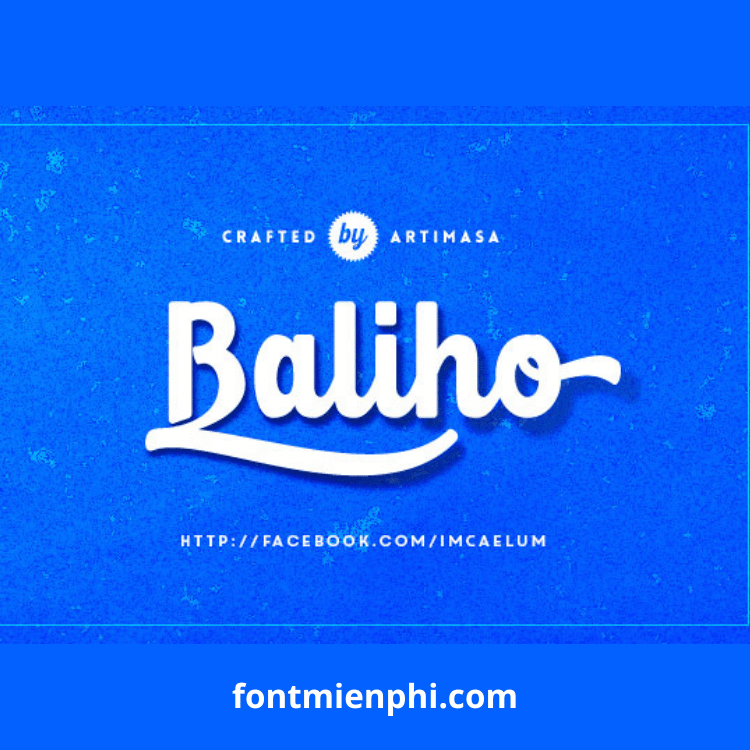
Việt hóa font iCiel Baliho Script
Font iCiel Baliho Script là một trong những font chữ nghệ thuật, phong cách brush script đẹp mắt, thích hợp cho thiết kế logo, poster, bìa sách, quảng cáo và các dự án sáng tạo khác. Bản Việt hóa của font này hỗ trợ đầy đủ dấu tiếng Việt, giúp người dùng tại Việt Nam dễ dàng sử dụng mà vẫn giữ nguyên nét đẹp mềm mại, tự nhiên của kiểu chữ viết tay.
Đặc Điểm Nổi Bật Của Font iCiel Baliho Script Việt Hóa
✔ Hỗ trợ tiếng Việt chuẩn – Được Việt hóa đầy đủ, đảm bảo hiển thị rõ ràng các ký tự có dấu.
✔ Phong cách nghệ thuật, sang trọng – Nét chữ mềm mại, phù hợp với thiết kế thời trang, quảng cáo, nhãn hiệu.
Kết Luận
Font iCiel Baliho Script Việt Hóa là lựa chọn hoàn hảo cho những ai yêu thích phong cách chữ viết tay nghệ thuật. Tải miễn phí ngay hôm nay tại Fontmienphi.com hoặc nâng cấp Member VIP để trải nghiệm kho font đa dạng và cao cấp!